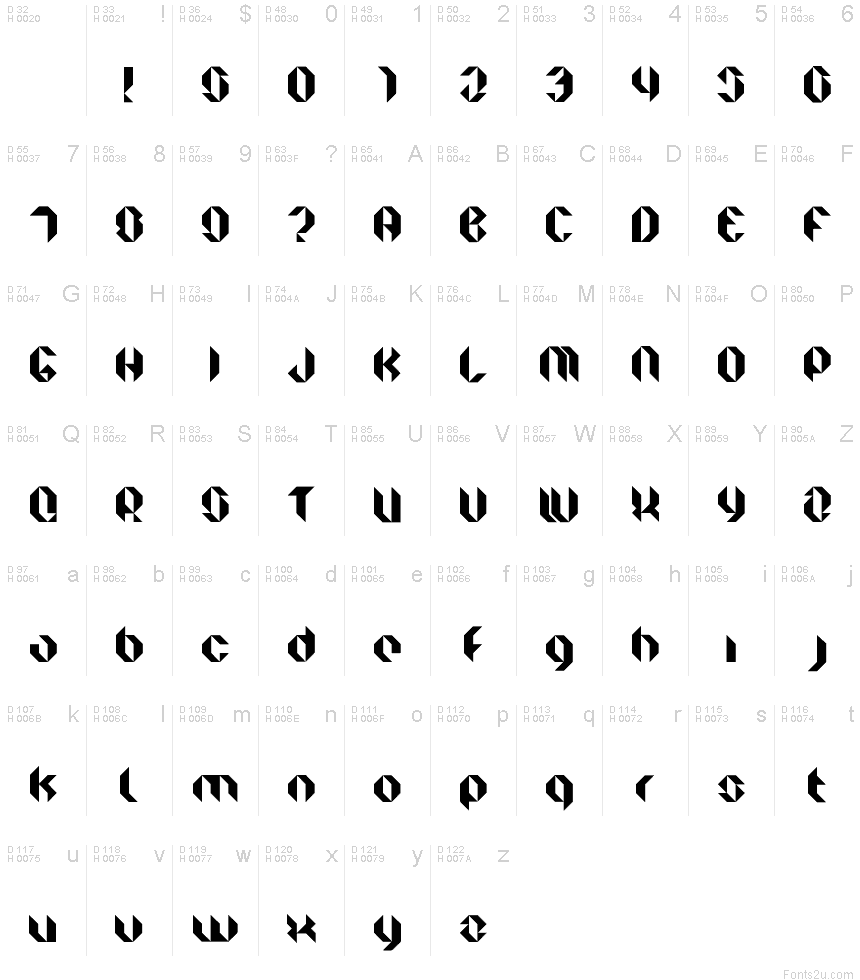
Facet Black, navržený Svetoslavem Simovem pro Fontfabric, je bezplatný, futuristický display font složený z ostře řezaných, fasetových písmen. Hrubé tahy, ostré diagonální řezy a úhlové mezery dodávají znakům vzhled ohýbaného kovu nebo technického emblému.
Skvěle se hodí pro technologický branding, herní loga, plakáty na akce, obaly alb a filmové titulky s nádechem sci-fi nebo industriálního stylu. Jako bezplatný font Facet Black nejlépe funguje v krátkých nadpisech a kompaktních logotypech, kde jeho dramatické prořezávané tvary mají dostatek prostoru pro definování kompozice.